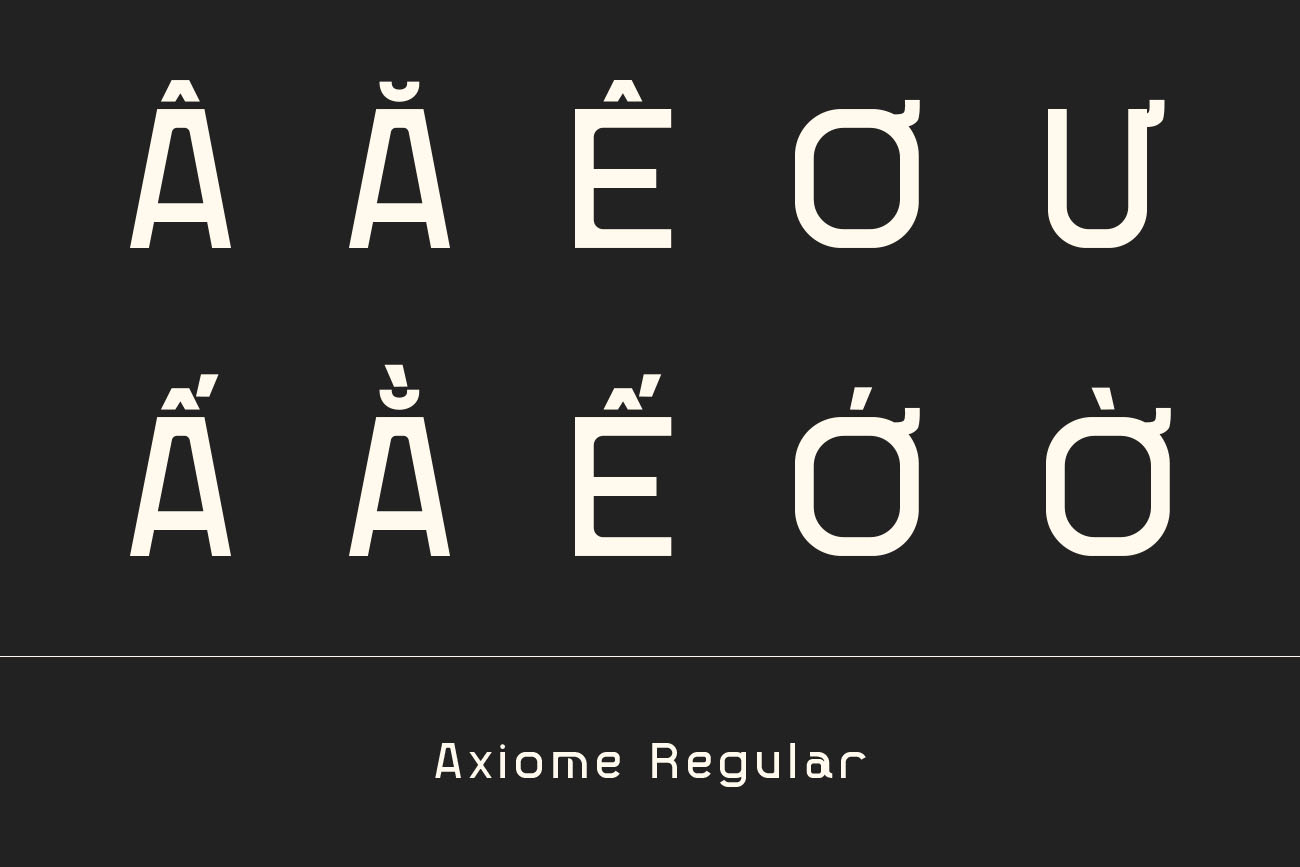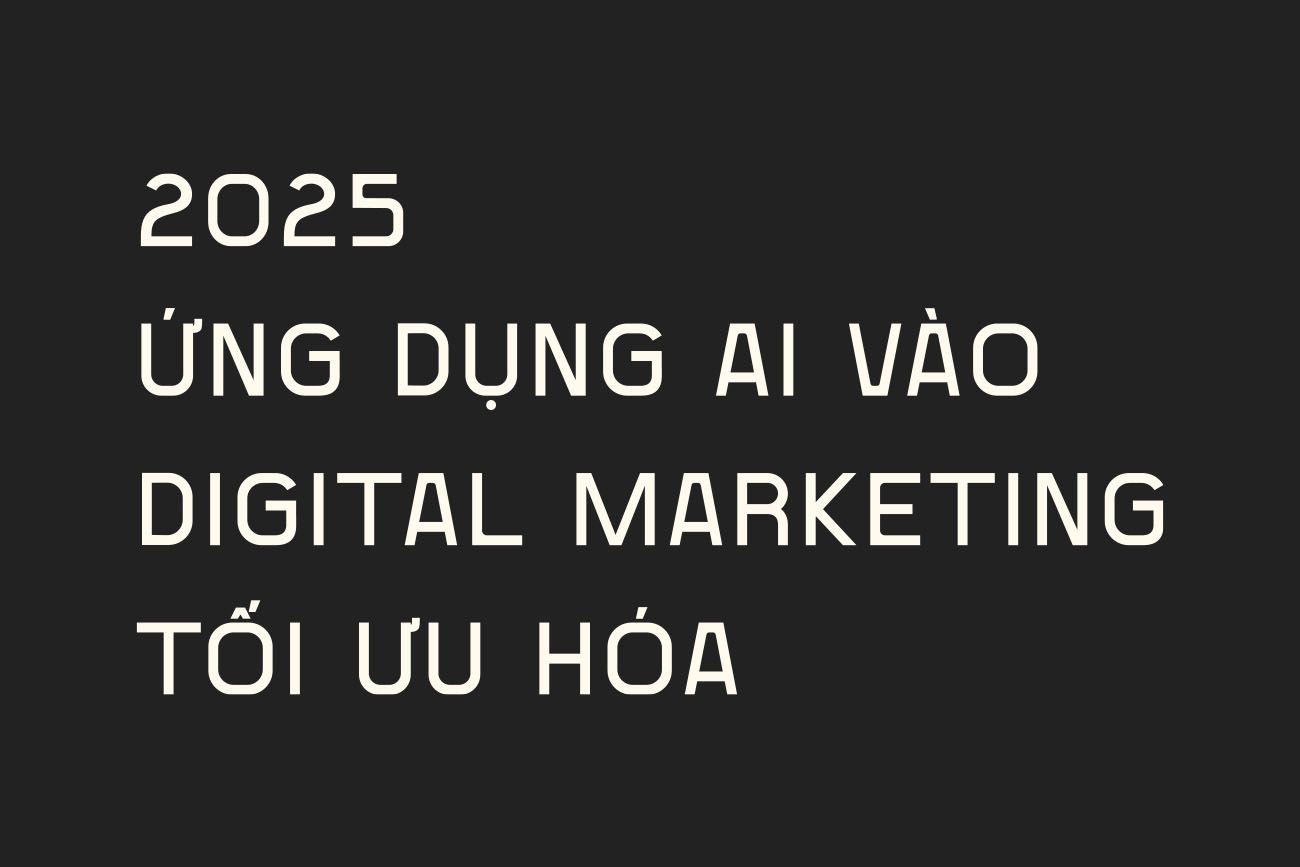
TH Axiome – Font chữ công nghệ hiện đại, tối giản Việt hóa
Tác giả Eko Bimantara
Axiome là một bộ font chữ công nghệ thuộc nhóm sans-serif hiện đại, được thiết kế bởi Eko Bimantara – một nhà thiết kế nổi tiếng với phong cách hình học sắc sảo và tối giản. Bộ font này mang đến cảm giác công nghệ, kỹ thuật nhưng vẫn giữ được nét thanh lịch, nhẹ nhàng trong từng ký tự.
Với đường nét gọn gàng, các cạnh chữ rõ ràng và bố cục cân đối, Axiome đặc biệt phù hợp với các thiết kế mang tính công nghệ cao như website startup, phần mềm quản lý, hệ thống UI/UX hoặc sản phẩm kỹ thuật số. Các chữ cái có độ dày vừa phải, khoảng cách được tinh chỉnh tốt, giúp font dễ đọc ngay cả khi hiển thị trên giao diện số.
Axiome không chỉ tạo ấn tượng trong phần tiêu đề, mà còn thể hiện hiệu quả trong phần nội dung nhờ khả năng hiển thị rõ nét trên mọi thiết bị. Bộ font hỗ trợ đầy đủ bảng chữ cái Latin và đã được Việt hóa hoàn chỉnh bởi Phạm Sơn, đảm bảo tương thích tốt với thiết kế tiếng Việt, không lỗi dấu, không vỡ ký tự.
Dù bạn đang thiết kế landing page công nghệ, hệ thống dashboard, brochure phần mềm hay logo thương hiệu kỹ thuật số – font chữ công nghệ Axiome sẽ giúp truyền tải thông điệp một cách chuyên nghiệp, hiện đại và chuẩn thị hiếu thẩm mỹ của người dùng thời đại số.